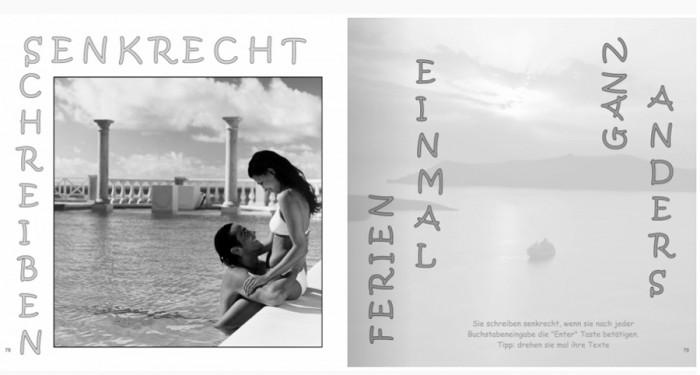
vertikal gesetzt - von oben nach unten
In der Gestaltung werden stets unzählige Faktoren gleichzeitig berücksichtigt und abgewogen. Vertikalsatz irgendwie generell verdammen zu wollen, kann da zu nichts führen. Es ist genauso albern, wie Versalsatz oder gesperrte Kleinbuchstaben generell zu verdammen. Es kommt halt auf den konkreten Fall an. Wenn wir aber keinen konkreten Fall vor uns haben, bringt die Diskussion auch nichts.
Edit: Aber eigentlich geht es um ein Logo, was ich nicht sehen konnte, weil es leider ganz schnell wieder gelöscht wurde.
Andererseits ist es aber, besonders in Ladenstraßen die einzige Möglichkeit, den Geschäftsnamen in möglichst großen Lettern in Richtung der Straße sichtbar und lesbar an der Hausfassade zu befestigen.
Ich erinnere z.B. von der Mönkebergstraße in Hamburg einige dieser Schriftzüge.
Und auch hier vertrete ich meine These.dass es für einen Geschäftsbetreiber gar nicht im Interesse liegt, den Lesefluss zu optimieren und so eher von einem unterbewussten Lesen, wie wir eben gut lesbare Texte fast schon nebenbei wahrnehmen, zu einer bewussten Handlung des Entzifferns zu kommen, wodurch sich dann eben nicht nur dieses Bild, sondern auch der Geschäftsname besser einprägt. Das gibt ja auch all diesen oft nur gerade so noch entzifferbaren Schriften, die oft für Ladenschilder verwendet und hier im Forum oft auch angefragt werden ihren Sinn. Und do ist eben auch dieses senkrecht schreiben ein Weg, dem Text hier eine mit einer Absichtshandlung verbundene Aufmerksamkeit zu geben, und gerade (gewollt oder auch nicht) das unbewusste Lesen zu bremsen
dann sind das wohl teileinheiten deiner these der unbewussten-lesens-bremse.
Ich kann mir nicht vorstellen, dass nur ein Werbetreibender sich sagt: » Ich habe eine ganz tolle Idee, lasst uns mal das Schild vertikal setzen – damit fordern wir den vielbeschäftigten, potentiellen Kunden auf, doch mal stehen zu bleiben und sich näher mit unserem Schriftzug zu befassen!« Das ist Quatsch ...
Die Begründung liegt doch zu nahezu 100% bei den technischen Möglichkeiten und den Bauvorschriften.
Solche Beschriftungen funktionieren doch, wie auch schon gesagt wurde, am ehesten bei kurzen Wörtern (Kino, Hotel, etc.) oder bei bereits erlernten Schriftzügen wie Karstadt.
Ichj behaupte na nicht, dass irgend ein Werbetreibender das so sagt, und mit dieser Begründung bestellt.
Fakt ist aber, dass rein gefühlsmäßig eher leseunfreundliche Schriften gern verwendet werden, und sich im Einsatz dann doch als erfolgreich erweisen, sonst würden sie ja auch nicht gewählt, und ich versuche nur den Umstand, das eben gerade schwerer lesbare Schriften oft erfolgreiche Werbeschriften sind zu erklären.
Gerade bin ich zweimal vierzig Minuten durch Berlin kutschiert worden, quer durch die Stadt, von Ost nach West und zurück. Auf dem Hinweg sah ich vier vertikale Fassadenbeschriftungen: Hotel, Hotel, Spielhalle, Parkhaus, alles in Versalien. Die ersten beiden in Prenzlauer Berg, eher billige Hotels, die Spielhalle in Mitte und das Parkhaus in Wilmersdorf. Auf dem Rückweg war es nur noch eine: Hotel, wieder in Prenzlauer Berg, billige Kette. Während der Fahrt ging es auch ein kurzes Stück über die Friedrichstraße, ein langes über die Kantstraße, auf der Rückfahrt über den Potsdamer Platz. Weit und breit kein vertikaler Satz außer den genannten Beispielen. Auf der Leipziger Straße gibt es aber eine vertikale Laufschrift. Da kann man schön erkennen, warum kein vernünftiger Gestalter so etwas macht. Ich fuhr im Schrittempo (Stau) daran vorbei und habe nicht herausbekommen, ob das Englisch oder Deutsch war, was da vertikal die Hauswand runterlief, geschweige, worum es überhaupt ging, ob das Kunst war (dann wäre es sowieso keine Typografie und folgte eigenen Gesetzen) oder Reklame. Auf dem Hinweg fuhr ich an einem aus einem Fenster hängenden gelben Lappen vorbei, auf dem stand STOP fracking. Von links nach rechts die Hauswand hoch. In einer Sekunde bequem gelesen. Vertikal gesetzt hätte ich nur STOP erkannt.
Fakt ist aber, dass rein gefühlsmäßig …
Ähm, was denn nun? Fakt oder Gefühl?
… eher leseunfreundliche Schriften gern verwendet werden, und sich im Einsatz dann doch als erfolgreich erweisen, sonst würden sie ja auch nicht gewählt …
Steile These. Das würde bedeuten, je hässlicher die Schrift, desto besser die Werbewirkung?! Ich fürchte, solch hellseherische Fähigkeiten haben die wenigsten Gewerbetreibenden. Und vielfach ist es gar nicht die Schrift, die den Ladeneingang verunstaltet, sondern die (vermeintliche) Typografie.
… das eben gerade schwerer lesbare Schriften oft erfolgreiche Werbeschriften sind …
Welches Beispiel hast du da im Kopf? Und wie stellt sich der Erfolg dar?
Na, da habe ich ja eine Diskussion entfacht.
Mir geht es um senkrechte Titel oder Headlines auf Papier - gesehen auf Einladungskarten, Visitenkarten, Broschüren, Buchcover, Bildbänden usw. Ich bin mir sicher, Ihr habt diese alle schon gesehen - da muss nix zitiert werden!
Und schon bin ich bei der berühmten Frage nach Henne oder Ei, wer/was war zuerst? Sind die Gestalter oder die Käufer dieser Drucke hausbackene und in typografischen Feinheiten ungelernte Bäcker, Frisöre oder Architekten (oh!)? Wer guckt nun von wem ab?
Oder ist es (etwa) jetzt in? Es gibt ja auch eine Lobby für das ß im Versalsatz.
Ich bin eben oldschool und wollte wissen, ob sich ein Trend abzeichnet. Die Tschicholdstelle werde ich suchen. Danke!
Wer hat mehr "historische" Textstellen für mich?
Man kann darüber streiten, aber in diesem Fall wird ja die chinesische Schreibweise zitiert, daher macht es in meinen Augen wieder Sinn. Ich find’s nicht schlecht.
Fündig wurde ich z.B. bei den Empfehlungen eines online-Dozenten zur Gestaltung von Fotobüchern …
Ich sehe hier keine Gestaltung, nur eine Entgleisung.
Ich sehe hier keine Gestaltung, nur eine Entgleisung
Und eine Randerscheinung? Hmm... Könnte es sein, dass Ihr diese "Entgleisungen" nicht beachtet, da niveaulos?